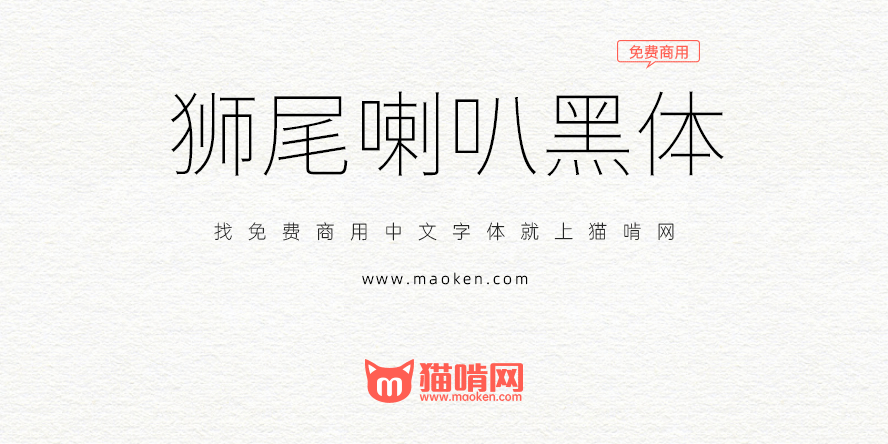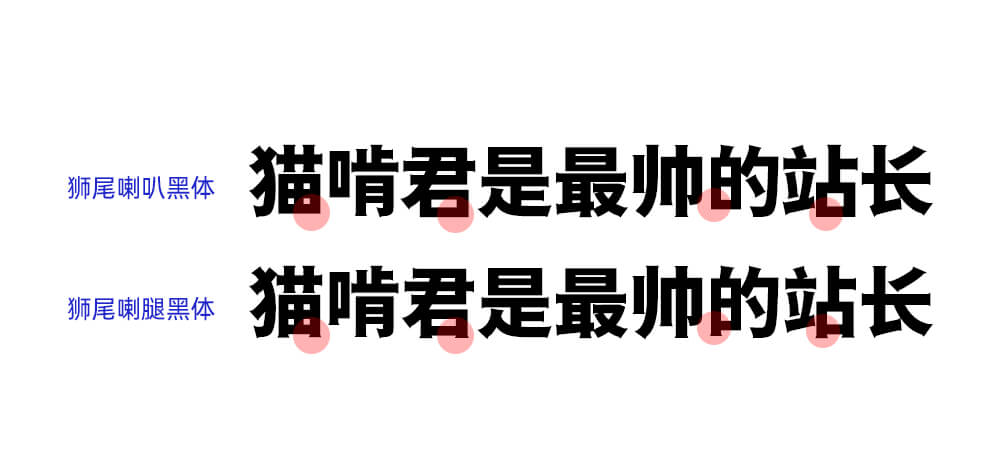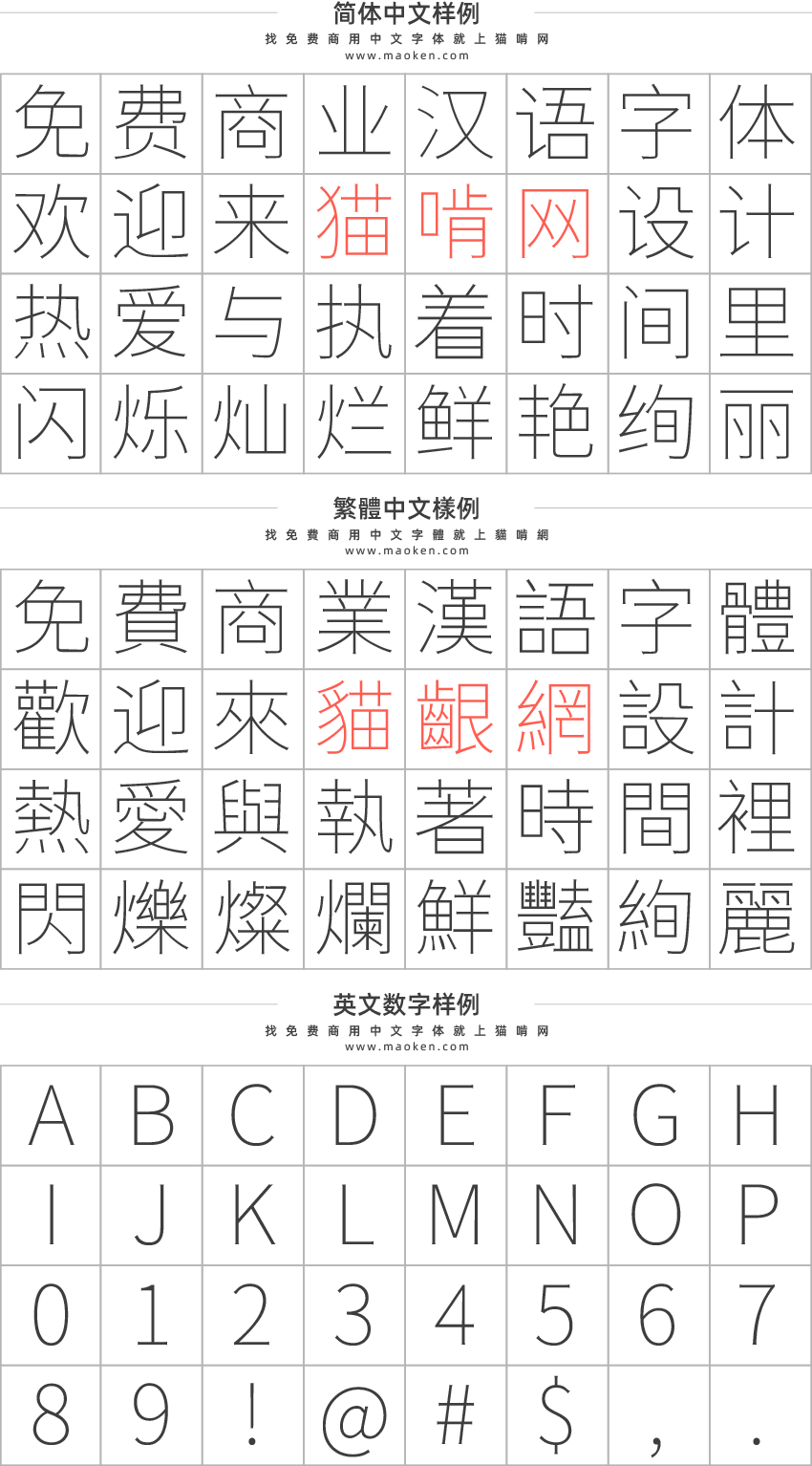
狮尾喇叭黑体基于思源黑体的笔触变喇叭口和拔脚改造,更加简明现代化的字体。支援简体中文、繁体中文、韩文与日文;可以免费商用,欢迎大家自由应用、自由优化、自由改作!
狮尾喇叭黑体的特色是:笔画的起头与收尾较宽,有喇叭造型。 「喇叭口」在铅字印刷时代有让印刷字安定清晰的用途,目前电脑萤幕显示与高解析度输出的数位时代,喇叭口变成字型的风格的一部份。
「狮尾喇叭黑体」与「狮尾喇腿黑体」差别在有没有拔脚,「拔脚」就是会有较少的笔画,例如移除「口」字的左右下角会多出的短线条。有拔脚的字会较圆,但是会造成有些字因直接去掉腿后左右不平衡、左右不对衬的「悬空」问题。改使用「腿」系列字体就不会有这个问题。